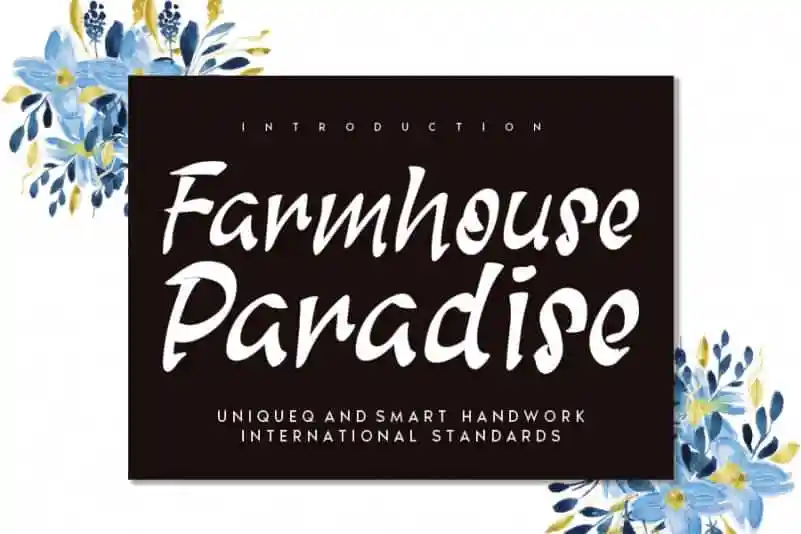
Farmhouse Paradise Brush Font – Download Grátis
A Farmhouse Paradise Brush Font é inspirada nas tipografias clássicas e traz seu próprio estilo único a qualquer projeto de design. Esta fonte script adora ser usada para criar cartões de visita, arte de estação, posts sociais chamativos e cartas de cumprimento fofas. Com uma sensação autêntica e encantadora, ela é perfeita para quem procura um toque delicado e aconchegante em seu design. Ideal para conjuntos românticos de casamentos ou para aqueles momentos especiais que precisam daquele toque de charme na web social ou nas cartas pessoais. Se você adora elementos rústicos e natureza, Farmhouse Paradise Brush Font é uma escolha perfeita para deixar seu design ainda mais especial e único.